Việc luyện viết chữ đẹp luôn là một trong những đề tài được nhiều thầy cô giáo, các bậc phụ huynh và các em học sinh quan tâm. Trong đó, cách viết chữ hoa sáng tạo đơn giản luôn là một trong những đề tài được quan tâm hết thảy bởi nó giúp cho việc luyện chữ trở nên dễ dàng hơn nhờ những nét viết uốn lượn không cầu kì. Trong chủ đề font chữ thuộc blog hỗ trợ hôm nay mình xin được hướng dẫn mọi người cách sử dụng cũng như các mẫu chữ hoa sáng tạo với phương pháp thực hiện khá đơn giản mà lại vô cũng đẹp bên dưới
Hướng dẫn cách viết chữ hoa sáng tạo đơn giản
Trước khi vào chia sẻ mọi người đang học viết cần phải ghi nhớ rằng để tiến được đến việc sáng tạo ra các chữ hoa thì chúng ta cần phải đi được bước đầu tiên đó chính là tập viết ở dạng cơ bản. Để thực hiện thì mọi người cần sử dụng vở có ô chữ như hình ảnh bên dưới và thực hiện theo các cấp (ở đây chia làm 3 cấp chữ khác nhau) như hình minh họa các bạn có thể xem ở phía bên dưới
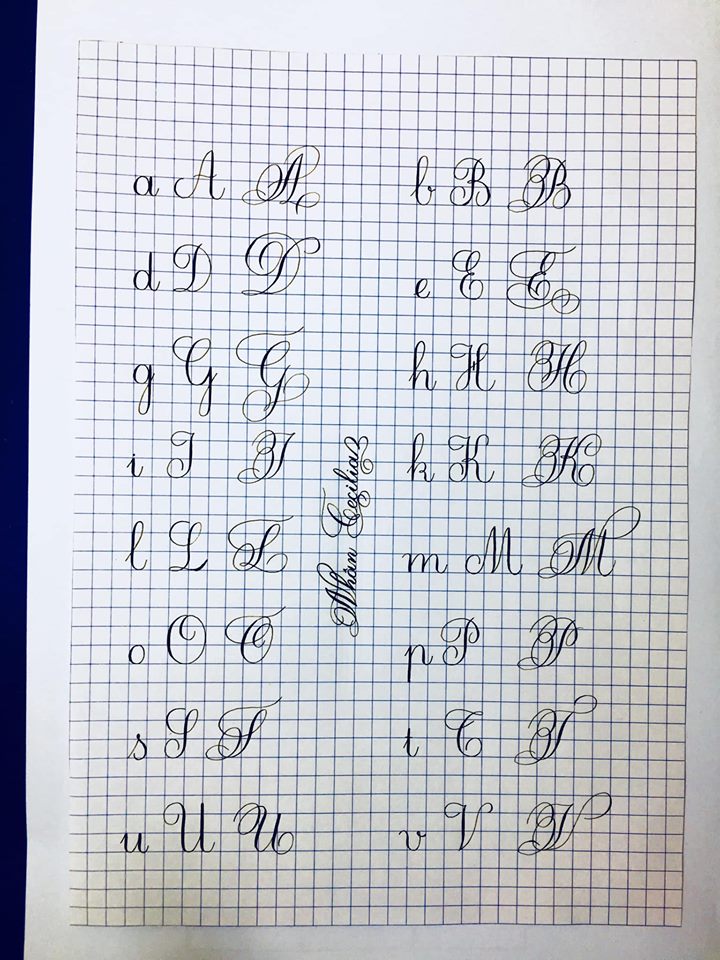
Tại đây mọi người có thể thấy rằng các nét vẽ được chia làm chữ hoa và chữ thường. Trong đó, độ phức tạp của chữ hoa cao hơn khá nhiều nhưng ngược lại thì chữ thường sẽ được sử dụng nhiều hơn là chữ hoa (bởi chữ hoa chỉ xuất hiện ở phần đầu của mỗi từ). Chính vì thế, để viết chữ hoa sáng tạo đơn giản thì việc làm duy nhất mọi người cần phải thực hiện đó chính là luyện song song cả 2 kiểu chữ này
Chữ viết thường đơn giản
Như đã chia sẻ ở phần trên thì việc viết chữ thường cũng là một trong những điều kiện không thể thiếu khi học viết chữ đẹp và cũng đều phải luyện thành thạo để có khả năng viết đúng chuẩn và đều đẹp (về phần này thì tùy thuộc vào từng người cũng như thói quen cầm bút sẽ có các kiểu chữ sáng tạo khác nhau. Thế nhưng theo nhìn nhận của mình thì có khá nhiều người sử dụng phương thức chữ nghiêng (nghiêng trái, phải), chữ thẳng đứng…
Thế nên để viết được chữ hoa sáng tạo đơn giản thì đầu tiên mọi người cần phải thực hiện viết chữ thường trước nhé!
Viết chữ hoa sáng tạo nhiều người dùng
Đối với việc viết chữ hoa thường đơn giản thì mọi người thường chú tâm hơn đến việc các chữ hóa sáng tạo bởi nó là bộ mặt của một từ trong câu và để sáng tạo ra một chữ hoa sáng tạo đẹp và đơn giản thì yêu cầu dành cho người viết cũng cần phải có kinh nghiệm luyện chữ và học hỏi nhiều mẫu viết khác nhau. Trong phần này mình sẽ chia sẻ đến mọi người các mẫu chữ hoa sáng tạo ở phần bên dưới của bài viết này
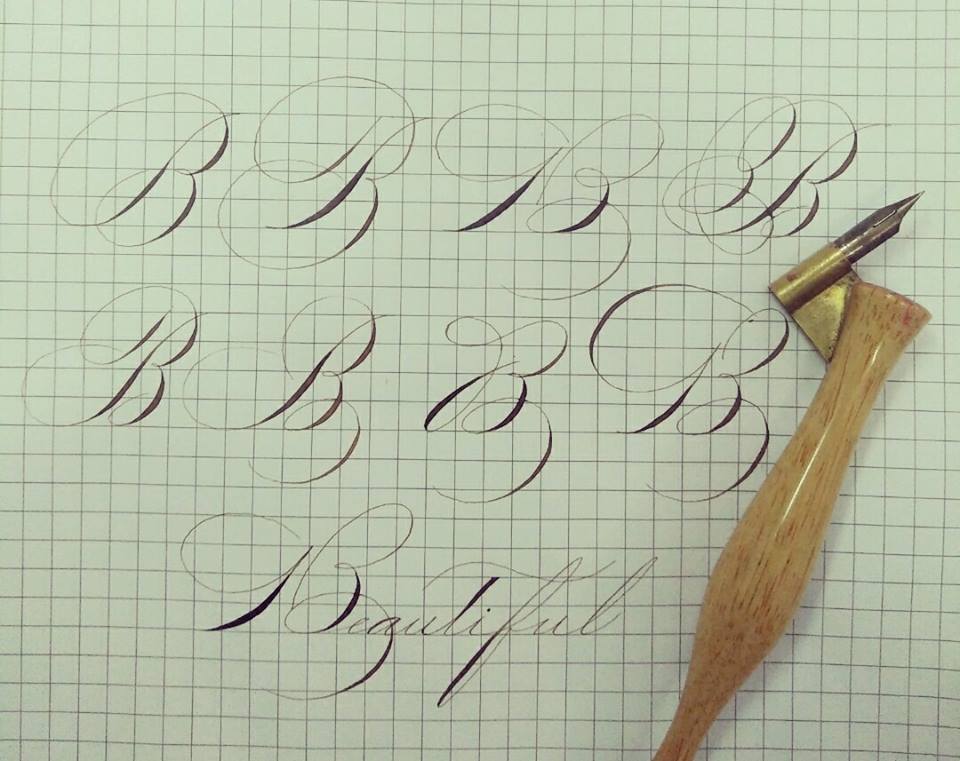
Như mọi người có thể thấy ở hình ảnh trên thì một chữ có rất nhiều kiểu sáng tạo khác nhau và mỗi chữ này cũng đều có những đặc điểm và nét đẹp riêng. Chính vì thế nên, viết chữ hoa sáng tạo cần 2 yếu tố chính đó là rèn luyện và kinh nghiệm học hỏi được từ bản thân và những người luyện viết xung quanh
Mẫu chữ thư pháp đơn giản nhiều người dùng
Đối với chữ thư pháp mọi người có thể thấy hình ảnh thông qua chuyên mục font chữ thuộc blog hỗ trợ đều có độ khó khá cao nhưng nó là được dựng sẵn và dùng trên máy tính. Nếu muốn luyện tay đến trình độ như vậy thì vẫn cần có thời gian rèn luyện và hiện nay thì có nhiều mẫu chữ thư pháp đơn giản, gọn nhẹ hơn chữ gốc rất nhiều mà mọi người có thể tham khảo
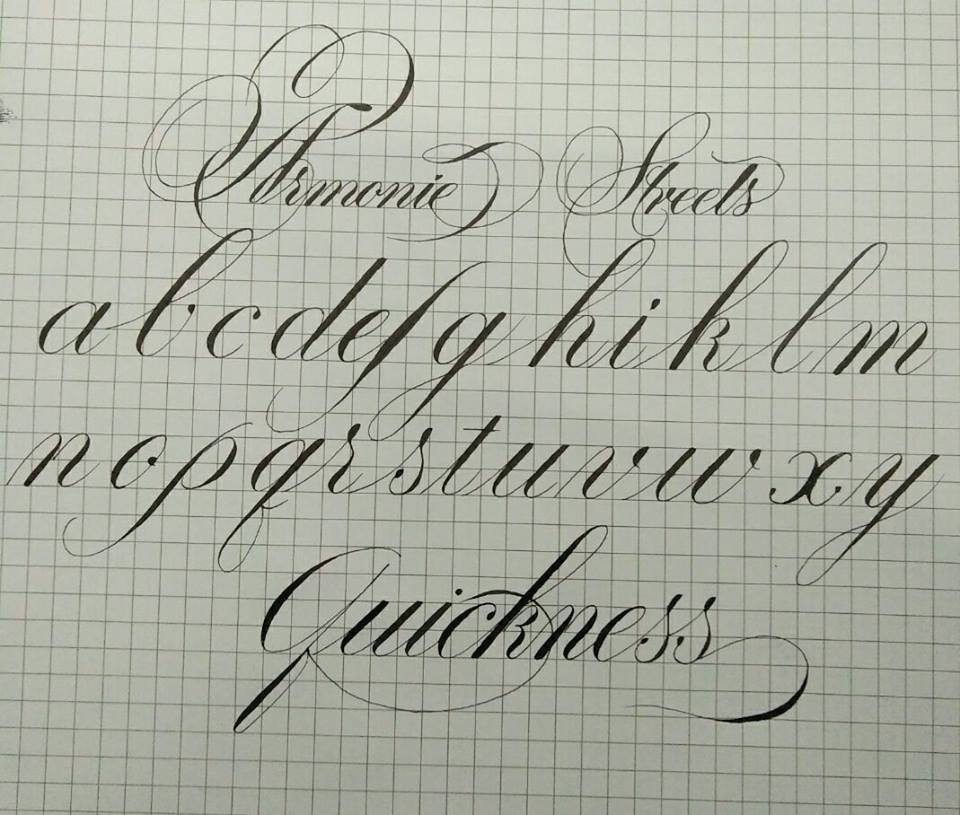
Đối với việc chữ thư pháp sáng tạo là cần thiết nhưng cốt lõi vẫn nằm ở cái hồn của từng nét vẽ và nếu như các bạn đang luyện cách viết này thì đừng quên phần quan trọng đó nhé. Nhất định sẽ thành công thôi à!
Các mẫu viết chữ hoa sáng tạo đơn giản, dễ học
Như đã chia sẻ ở trên thì ở phần này là những hình ảnh về các mẫu chữ hoa lẫn các chữ thường đơn giản để mọi người có thể rèn luyện cũng như học hỏi thêm kinh nghiệm từ nhiều người đã thực hiện trước đó. Nếu thấy chữ nào đẹp lại đơn giản và dễ thực hiện thì làm luôn cho nóng nhé! Cũng đừng quên lưu bài viết này lên tường nhà mình để mỗi lần học có thể lôi ra và thực hiện luôn cho đỡ quên
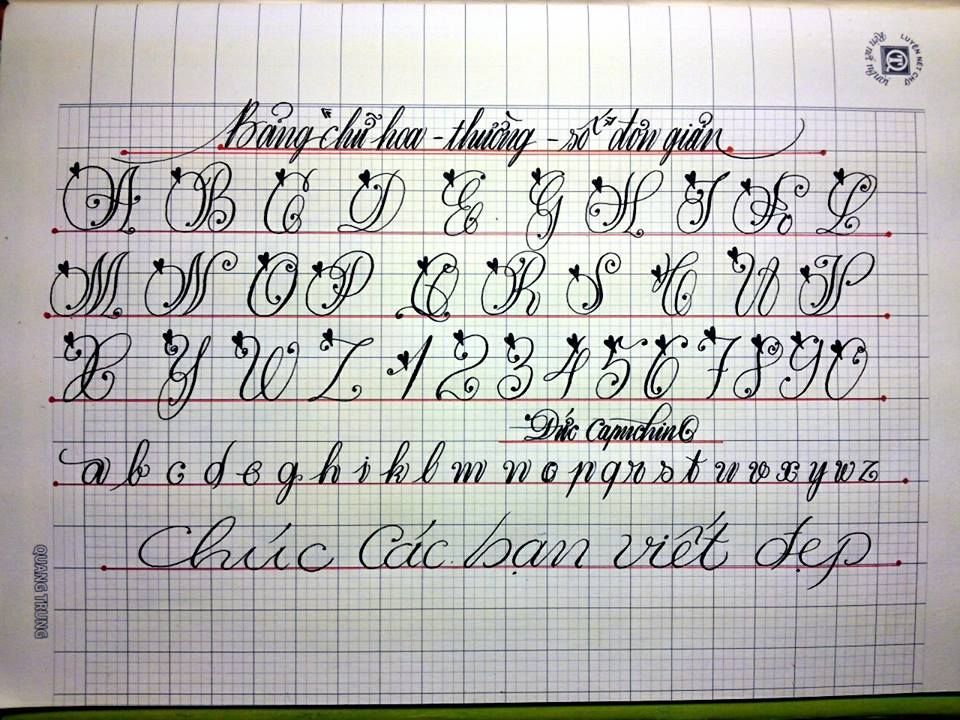
Đây là bảng chữ cái viết hoa, viết thường và số đơn giản mà mọi người có thể sử dụng để viết chữ đẹp
Chữ viết sáng tạo đơn giản siêu đẹp
Tổng kết